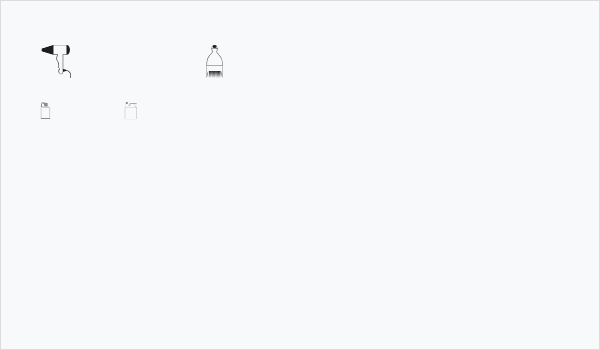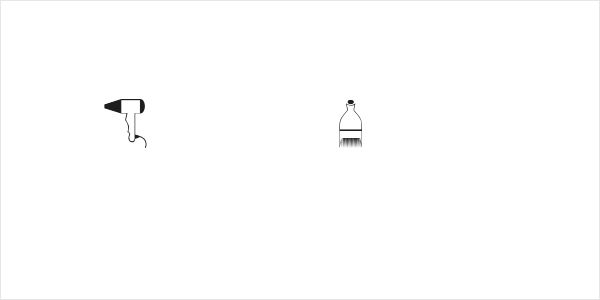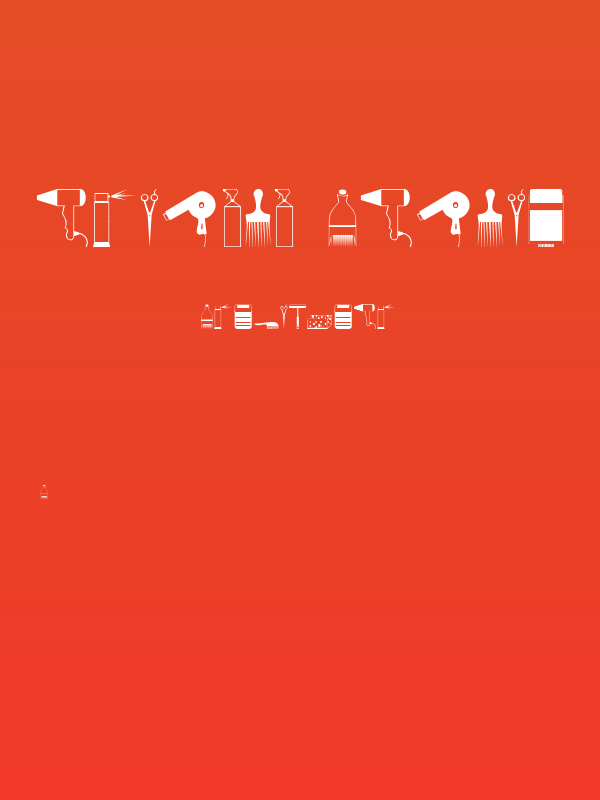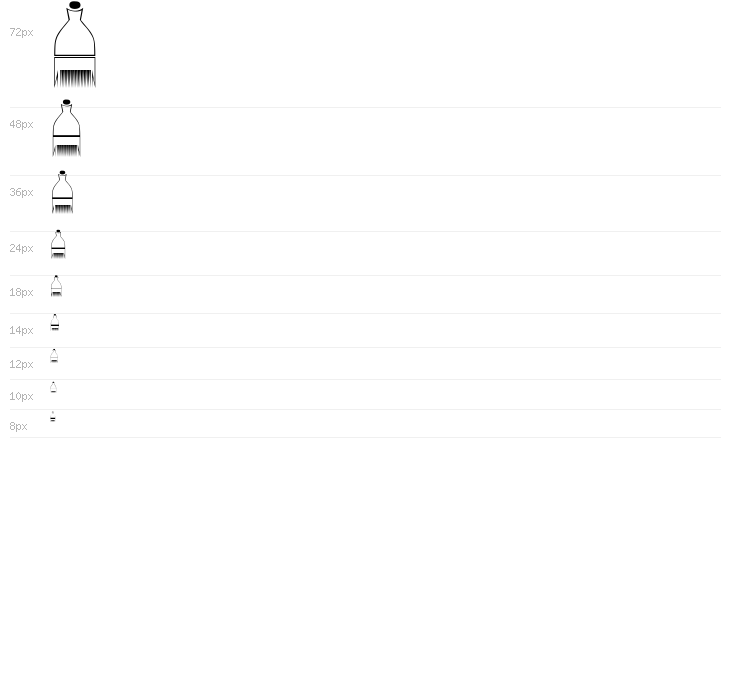
Hygiene Things Font
| Stile generale | Decorative, Playful, Thematic |
| Caso d'uso | Logos, Posters, Educational Materials, Themed Graphics |
| Progetti proposti | Children's educational materials, posters for bathrooms or salons, infographics about hygiene, themed event invitations. |